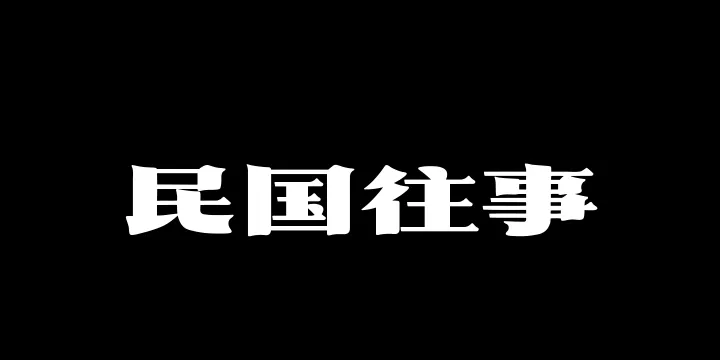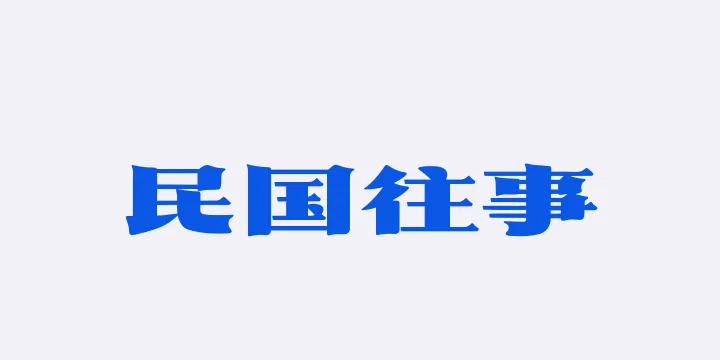
山海民国往事W By 山海字库 商用字体
字体全名: 山海民国往事W
字体简介: 山海民国往事,包含简繁汉字9169个,符号200+个。该字体灵动质朴,字形宽大,造型兼具硬朗与圆润的特点,直线与曲线的完美结合,构成棱角分明、坚实有力的结构造型,在笔画交错间展示出民国时期的民国风字形特点。
所属分类: 宋体